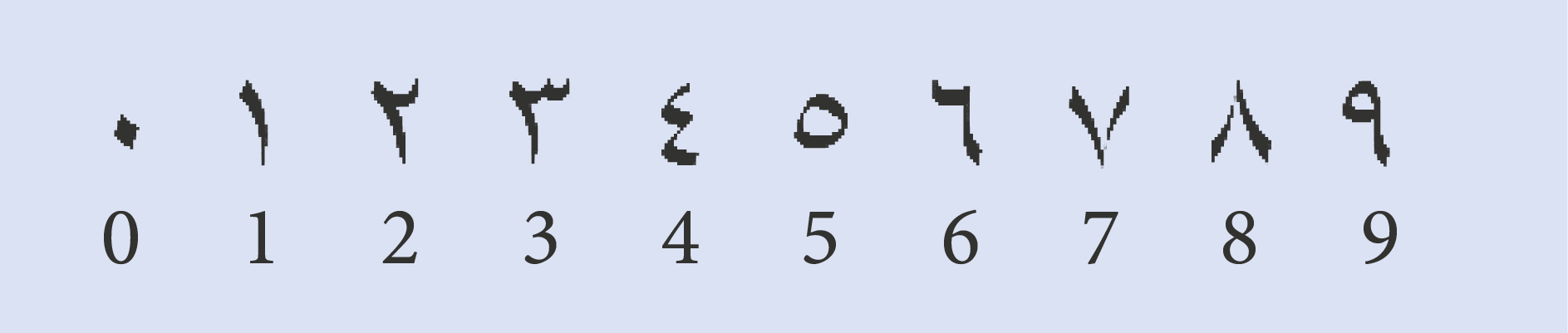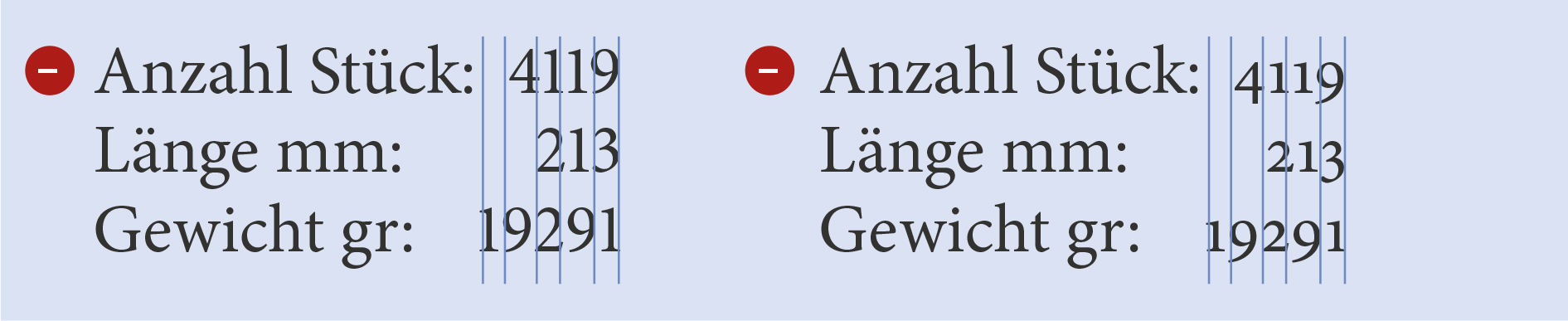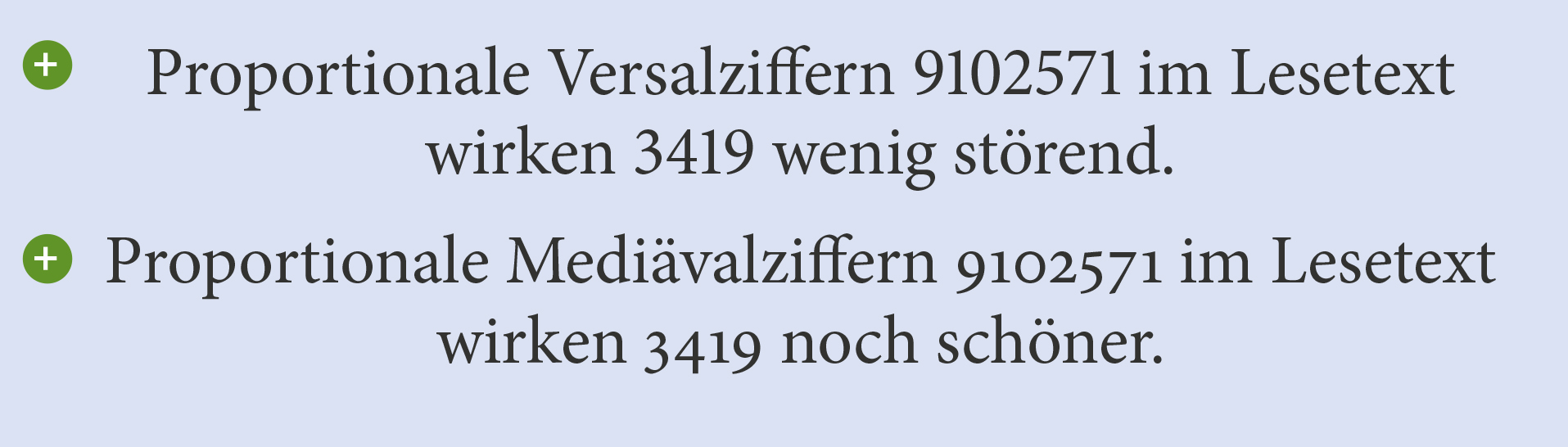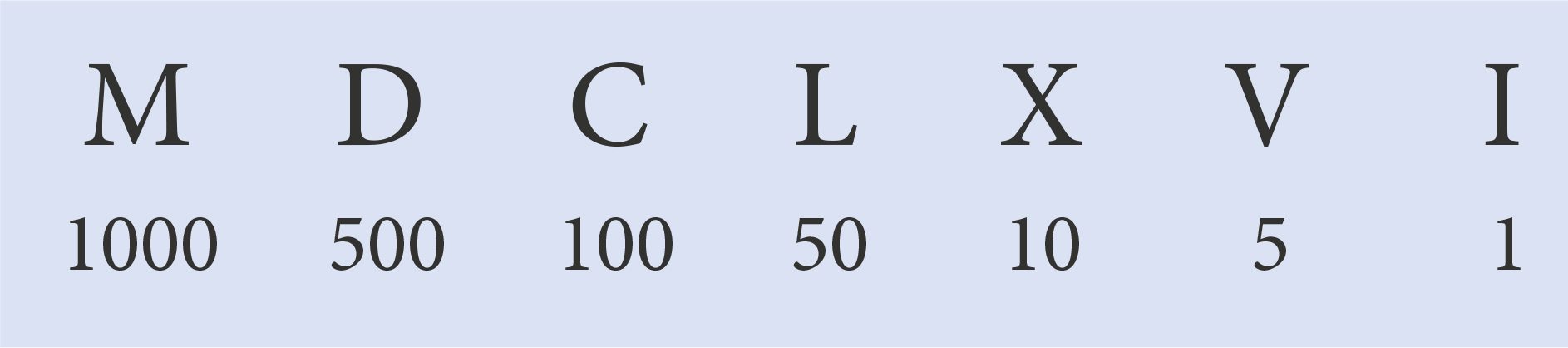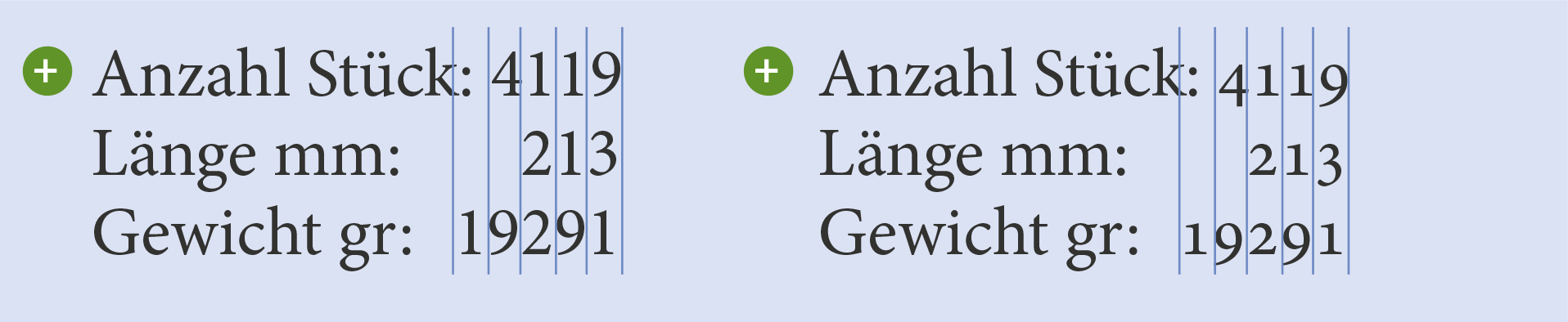
Tabellenziffern, Proportionalziffern, Mediävalziffern, Versalziffern: Ziffern und Zahlen in der Typografie
In der Typografie gibt es eine Menge unterschiedlicher Möglichkeiten, Ziffern und Zahlen darzustellen: Römische und arabische Ziffern, Mediävalziffern und Versalziffern stehen Kommunikationsdesigner zum Beispiel zur Verfügung, um Texte und Zahlen ansprechend zu gestalten. Worin die Unterschiede der Zahlenschreibweisen liegen und welche Darstellung sich für welchen Einsatz eignet, das möchte ich in diesem Blogbeitrag kurz besprechen.
Haben Sie sich schon einmal gefragt, wieso wir römische Schrift schreiben, aber arabische Ziffern verwenden? Nun, das liegt daran, dass die römische Schrift in diesem Sinne gar keine Zahlen kennt. Sie verwendet Buchstaben aus dem Alphabet als Zahlensystem. Deshalb gehören die Buchstaben, die aus dem Alphabet kommen, zur römischen Zahlenschrift. Sie ist seit der Antike bekannt und wird auch als additives Zahlensystem bezeichnet.
Römische Zahlenschrift
Dieses Zahlensystem ist einigen von uns sicher noch aus den Lateinunterricht bekannt. Es wird heute nur noch für Schreibweisen von Geschichtszahlen, Urkunden oder als Aufzählungszeichen zur Nummerierung von Texten verwendet. Es eignet sich jedoch weniger gut, um damit mathematische Rechenoperationen durchzuführen. Deshalb wurde dieses additive Zahlensystem im 11. Jahrhundert durch die arabischen Ziffern abgelöst.
Römische Zahlen in der Typografie
Arabische Ziffern
Die arabischen Zahlen besitzen ein Stellenwertsystem. Es ordnet jeder Ziffer einen Wert zu – in Abhängigkeit von ihrer Position innerhalb der Zahl. Mathematische und naturwissenschaftliche Berechnungen können damit wesentlich einfacher durchgeführt werden. Ursprünglich kommt das arabische Zahlensystem aus Indien. Kaufleute haben es vermutlich im 9. Jahrhundert nach Arabien gebracht. Ab dieser Zeit hat die Schriftdarstellung viele Umformungen erlebt – bis sie die heute bekannte Schreibweise erreicht hat. Über die Mauren gelangten sie im 11. Jahrhundert über Spanien nach Europa.
Arabische Zahlen in der Typografie
Mediävalziffern
Sicherlich haben Sie schon mal von den Mediävalziffern gehört oder sie bereits in der Typografie angewendet. Mediävalziffern haben – genau wie die Buchstaben im Alphabet – eine Oberlänge, Mittellänge, Unterlänge und eine Schriftlinie. Deshalb eignen sie sich besonders als Schreibweise in der Lesetypografie, weil Zahlen im Text als eher störend für den Lesefluss empfunden werden. Das Wort „Mediäval“ stammt vom lateinischen medius (mittlere) und aevum (Zeitalter). Gemeinsam mit den arabischen Ziffern sind die Mediävalziffern über Spanien nach Europa gelangt.
Beispiel für Mediävalziffern
Ziffern in der Typografie
Wir verwenden also in der Typografie arabische Ziffern, die wir mit Versalziffern oder Standardziffern und Mediävalziffern bezeichnen. Hier die beiden Typen im direkten Vergleich:
Versalziffern oder Standardziffern:
Beispiel für Versalziffern
Mediävalziffern:
Beispiel für Mediävalziffern
Proportionale Versalziffern und Mediävalziffern
Die proportionalen Ziffern haben im Vergleich zu den Standardziffern eine unterschiedliche Schriftbreite – vergleichbar mit denen der normalen Buchstaben. Sie eignen sich deshalb besonders als Zahlen im Lesetext, weil sie gemeinsam mit den Wörtern ein harmonisches Schriftbild ergeben:
Proportionale Ziffern im Fließtext
Versalziffern und Mediävalziffern für Tabellen
Darüber hinaus betrachten wir in der Typografie Versal- und Mediävalziffern für Tabellen gesondert. Im Gegensatz zu den proportionalen Ziffern haben die Tabellenziffern die gleiche Schriftbreite. Sie eignen sich besonders gut für Schreibweisen in Tabellen – also dann, wenn Zahlen geordnet untereinander stehen. Proportionale Versalziffern und Mediävalziffern hingegen eignen sich nicht für Tabellen:
Tabellenziffern richtig angewendetTabellenziffern falsch angewendet
Mein Typo-Assistent Zitzero
Proportionale Versalziffern und proportionale Mediävalziffern
Aufgrund ihrer unterschiedlichen Proportionen bei der Schriftbreite (wie die der Buchstaben) verwende ich diese Ziffern gerne als Schreibweise bei Zahlen im Lesetext, beispielsweise für Geschäftsberichte.
Proportionale Versal- und MediävalziffernProportionalziffern im Fließtext
Versalziffern für Tabellen und Mediävalziffern für Tabellen
Da die Schriftbreite dieser Zahlen immer gleich breit ist, verwende ich diese Schreibweise immer dann, wenn Zahlen in Tabellen oder sonst wo geordnet untereinander stehen sollen.
Versal- und MediävalziffernBeispiel für Tabellenziffern
In der Regel verwendet das Programm als Standardzahlenformat die Versalziffern für Tabellen. Sie können dieses Ziffernformat aber ändern in: InDesign -> Menü: Schrift -> Zeichen. Es öffnet sich dann das Bedienfeld Zeichen. Klicken Sie dort oben rechts auf Optionen einblenden und gehen Sie dann auf Open Type. Ganz unten finden Sie die unterschiedlichen Ziffernarten. Beachten Sie, dass Mediävalziffern nicht immer in jeder Schriftart vorhanden sind.